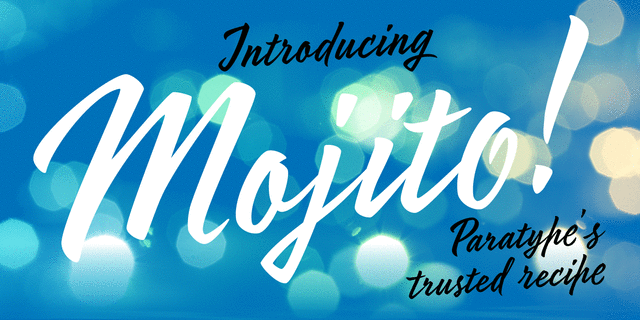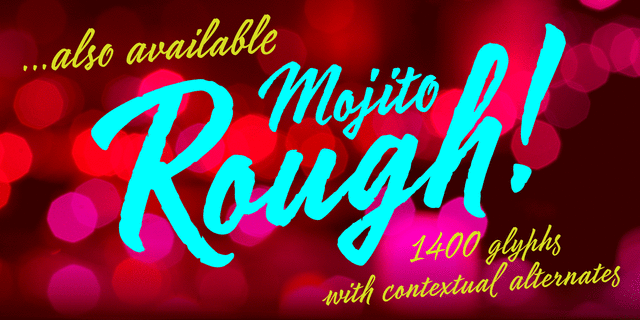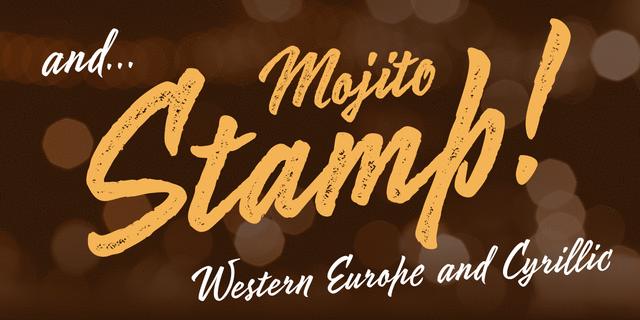
Mojito — живой и бодрый каллиграфический шрифт на основе письма круглой кистью (брашпеном). Автор тщательно переосмыслил форму всех знаков и нарисовал очень лаконичный, точный и чистый контур, который будет прекрасно выглядеть при любом увеличении. В Mojito около 1400 знаков, в том числе альтернативы, лигатуры, начальные и конечные формы. Благодаря этому буквы не повторяются, а их сочетания выглядят максимально естественным образом, особенно в кириллице. При наборе одними прописными буквами в Mojito можно включить замену основных форм знаков на упрощённые, спроектированные специально для этой цели. Два дополнительных начертания имитируют письмо по шероховатой поверхности и оттиск высокой печати. Mojito прекрасно подойдёт для упаковки и рекламы, продуктов и напитков, кафе и ресторанов, крафтовых и рукодельных вещей, детских книг, журналов и т.д. Шрифт спроектирован Захаром Ящиным и выпущен компанией Паратайп в 2017 году. Дополнительные начертания подготовлены Александром Любовенко.